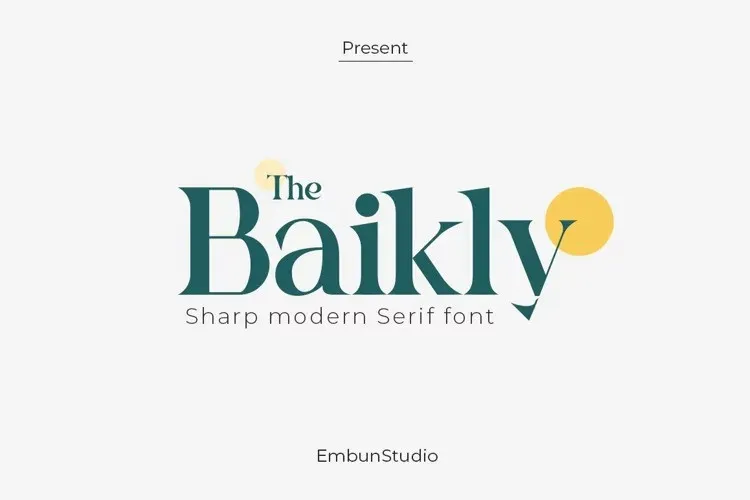
A fonte ‘The Baikly Font’ é uma elegante tipografia serif, criada pela embuntype inspirada na profundidade e antiguidade do Lago Bajkal, a mais profunda e mais velha lago do mundo localizado no extremo sul da Rússia. Esta fonte não apenas remete aos encantos geográficos desse lago místico, mas também oferece uma experiência visual envolvente que cativa os olhos dos leitores. Seja em um livro de ficção imaginativa ou na capa de um romance histórico, a The Baikly Font traz profundidade e detalhes para qualquer projeto gráfico. Seu design sofisticado e sua característica serif garantem uma aparência elegante e perfeita para textos formais, tornando-a uma escolha ótima para designers que buscam personalidade em seus projetos de texto.